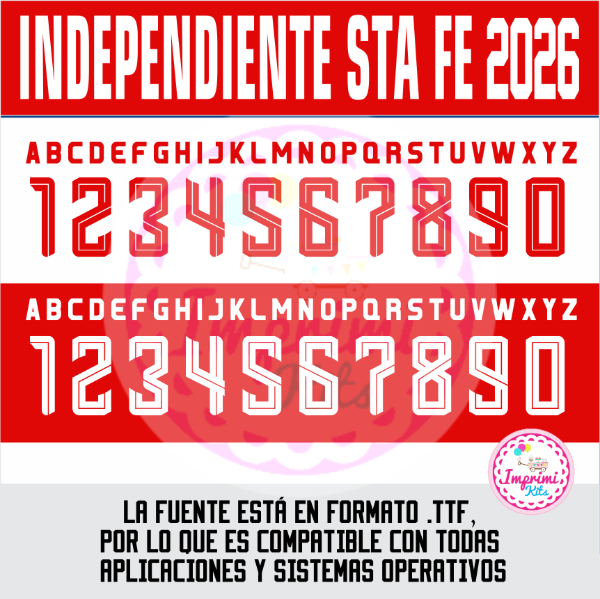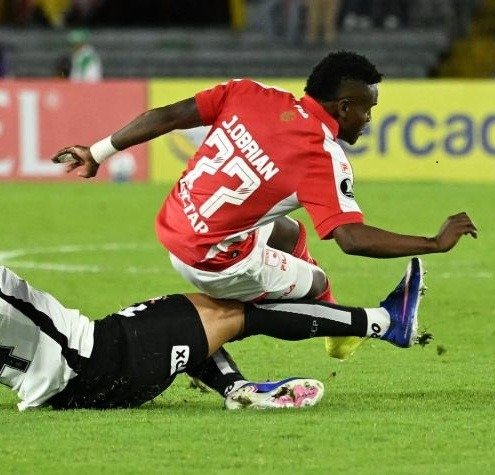
Tipografia Camiseta Ttf Otf Numeros Dorsal INDEPENDIENTE DE SANTA FE 2026
Tipografía Números Fuente
Realizá todo tipo de creaciones con la tipografía utilizada actualmente en el club